今日は、いつもの記事とは少し違って、子どもたちが硬筆展覧会に向けて練習した成果をご紹介します。
左は練習を始めたときの一枚目、右は最後に仕上げた作品です。
一人ひとりが丁寧に書くことに向き合い、驚くほどの変化を見せてくれました。
どの作品も、その子自身のがんばりと集中のあとがしっかり伝わってきます。
それではご覧ください!
小学4年生
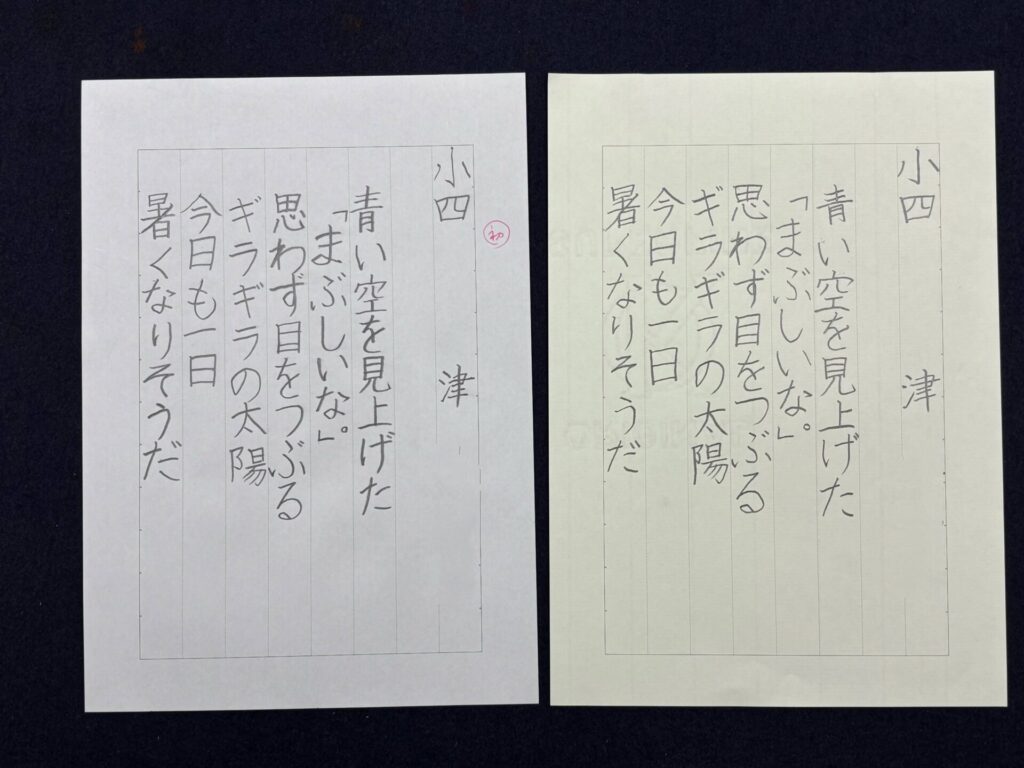
字の太さのムラがなくなり、全体が整いました。
特に「目」や「陽」の文字がていねいにそろい、読みやすくなっています。
小学6年生
字のバランスが整い、自信をもって書けるようになりました。
「生活にうるおいと」の部分が自然につながり、流れのある字になっています。
小学2年生
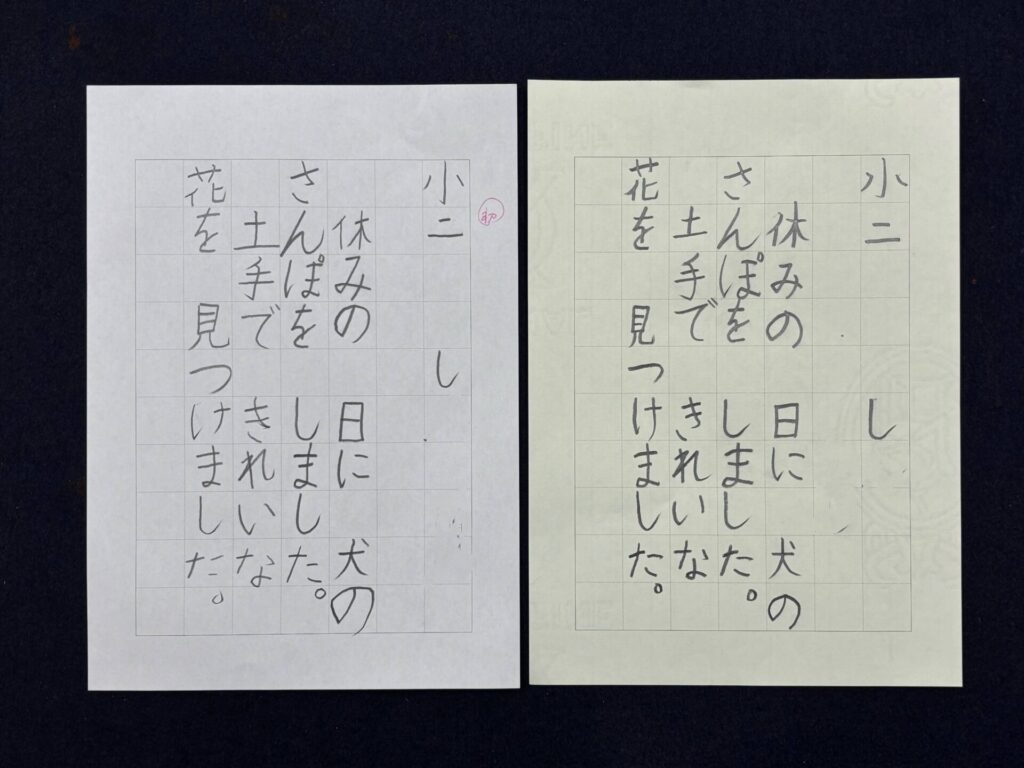
一字一字を丁寧に書こうとする姿勢が感じられる仕上がりです。
「休みの日に」がまっすぐ並び、読みやすさがぐんと上がりました。
小学6年生
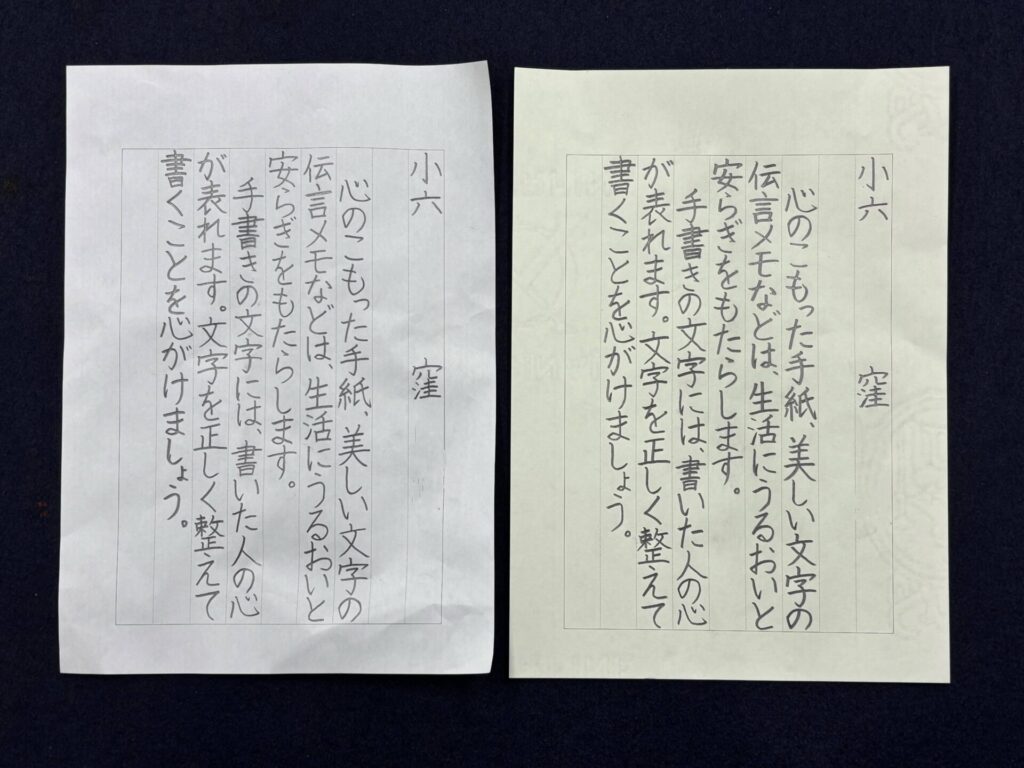
「手書きの文字には…」の一文が特に美しく、字の形がそろって安定感が出てきました。
落ち着いた印象の仕上がりです。
小学6年生
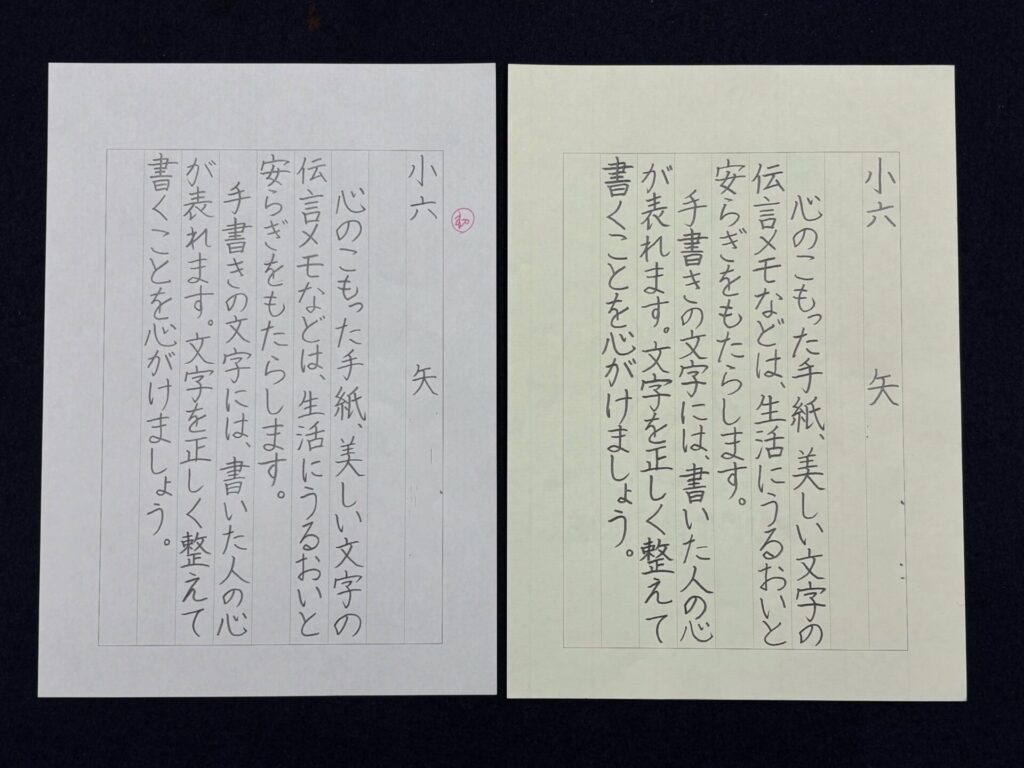
字の太さや形が安定し、一文字一文字に気持ちがこもっています。
「手書きの」の行はとてもていねいで、全体を引き締めています。
小学6年生
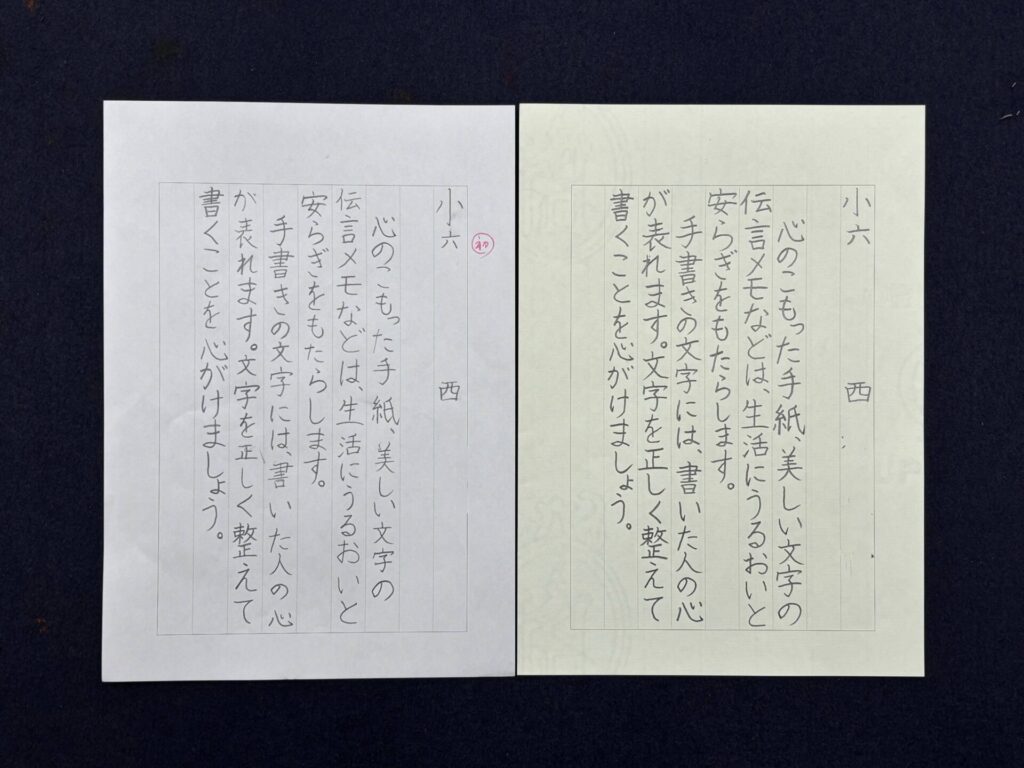
漢字は大きく、ひらがなは小さくと、字の大きさのバランスがとてもよくなりました。
一文字ずつ丁寧に書こうとした様子が伝わってくる、落ち着いた作品になりました。
書くことで見える「成長の過程」
作品を比べてみると、字の形や大きさだけでなく、取り組む姿勢そのものが大きく変わっていることに気づかされます。
「もっとこう書きたい」と思いながら練習を重ねた時間が、しっかりと紙の上に残っています。
またひとつ、自分の力でできることが増えた子どもたち。
これからもそんな積み重ねを、大切にしていきたいと思います。